网页设计用什么字体?精选12款免费可商用字体推荐
刚开始做网页设计时,我最头疼的就是选字体。电脑里装了几百种,但真到用时,不是担心版权问题,就是感觉效果不对。页面看起来要么太花哨,要么太死板。
做好网页设计,问题的核心不在于字体数量的多少,而在于是否掌握了合适的选择逻辑。分线一批既好看又免费、还能商用的字体。
鸿雷小纸条青春体
鸿雷小纸条青春体是设计师鸿雷创作的、精准还原学生时代课间随手传写小纸条质感的青春向专属手写字体。这款字体完全复刻了年少时在草稿纸、便签上走神涂写的自然状态。
鸿雷板书简体
鸿雷板书简体是由字体设计师鸿雷打造的一款高度还原真实黑板书写质感的实用型手写字体,专门复刻了日常教学场景里粉笔板书的自然书写状态。
整体风格亲切接地气,自带浓厚的校园怀旧氛围,松弛又有氛围感,完美复刻了大家学生时代课堂上熟悉的书写记忆。
演示佛系体
演示佛系体是一款主打松弛治愈氛围的创意手写字体,。这款字体完全弱化了常规字体的锋利棱角与规整约束,所有笔画的起笔、收笔和转折处都做了圆润化处理,没有丝毫尖锐感,笔画粗细均匀柔和,字形结构刻意打破了标准化排版的严丝合缝,带着轻微的、随性的错落感,仿佛是放松状态下随手书写的字迹,自带慢悠悠的松弛感。
霞鹜文楷
霞鹜文楷是一款让我眼前一亮的楷体。它比传统楷体更工整,在屏幕上显示非常清晰,自带一种温润的人文气质。
适合用在文化、艺术、教育类网站。可以用在段落开头、引言块,或者作为次要标题,能瞬间提升网站的格调。
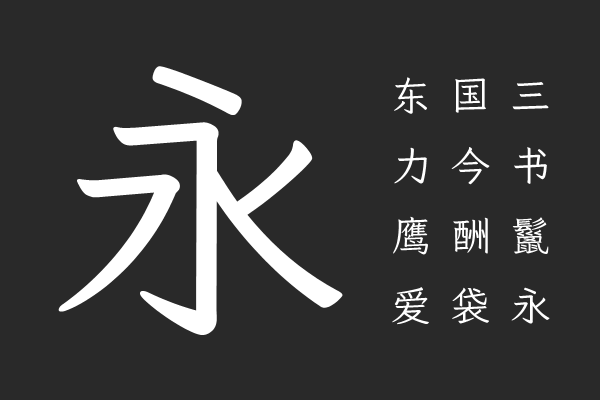
得意黑
得意黑它属于窄斜体,有点复古,有点未来感,造型非常独特。适合用在需要突出个性的标题、海报 Banner、数字展示。它不适合大段正文,但作为视觉焦点,效果极其出众。
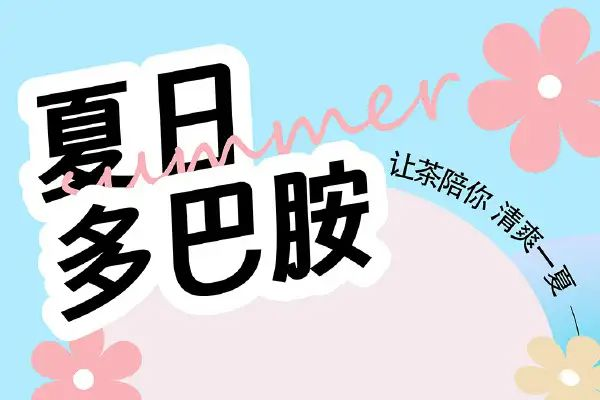
联盟起艺卢帅正锐黑体
联盟起艺卢帅正锐黑体是一款力量感很强的标题字体,笔画粗壮有力,充满自信。适合游戏、电竞、运动或男性化品牌网站的标题。用它做主标题,能立刻传递出强有力、果断的感觉。
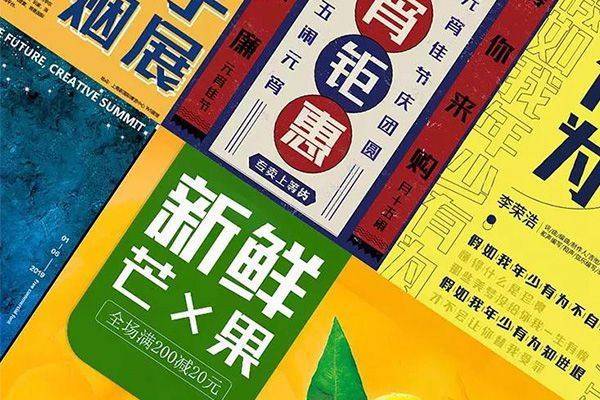
站酷快乐体
站酷快乐体笔画圆润,充满手写的随意感。适合儿童、母婴、休闲食品、社群活动类网站。用在按钮或一些提示性文字上,能增加页面的友好度和趣味性。
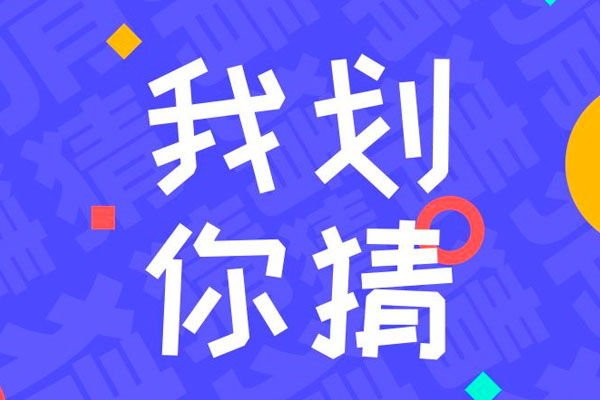
站酷小薇 LOGO 体
站酷小薇 LOGO 体是非常精致的一款字体,笔画细而有力,有点像高级品牌的 logo 常用字体。
适合用在哪儿:副标题、导航栏、卡片标题,或者需要体现精致感的短句。它能让细节之处也显得很有设计感。
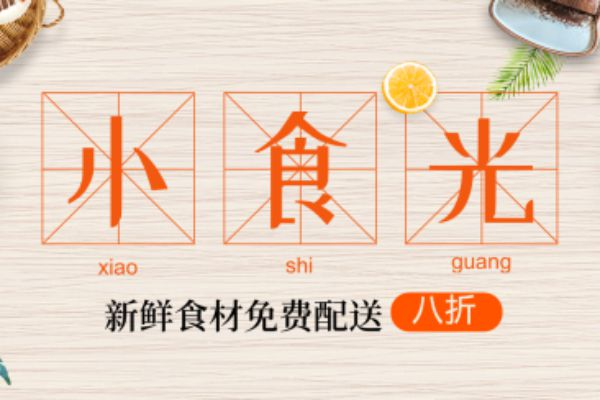
江西拙楷
江西拙楷体字体有真实的手写笔触,质朴又自然,能让人感受到温度。适合个人博客、独立设计师网站、手工艺品店铺。
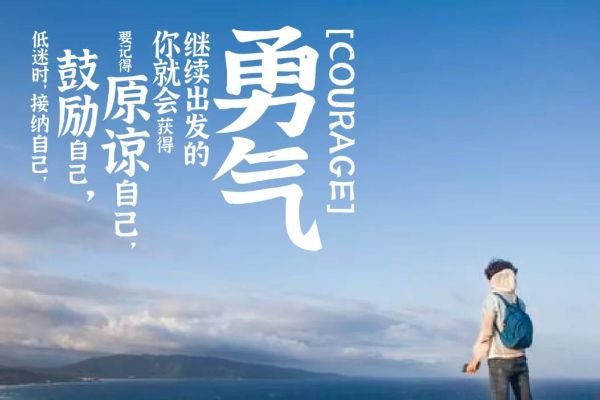
OPPO Sans
OPPO Sans是一款专门为屏幕阅读优化的字体。中宫开阔,字形均衡,长时间看也不会累。
适合内容量大的资讯站、阅读类应用、后台管理系统。它的核心优势就是极佳的屏幕可读性。
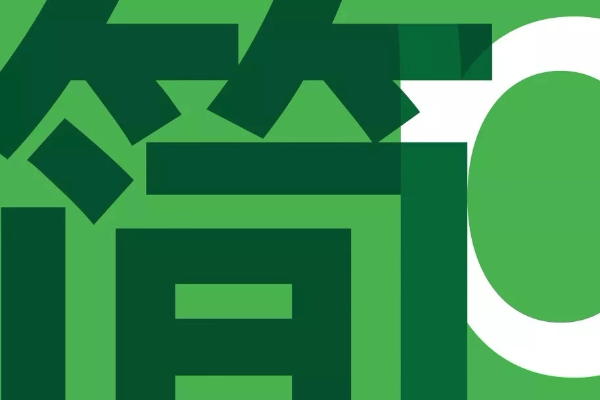
阿里妈妈数黑体
阿里妈妈数黑体是一款专门为数字显示设计的字体。数字的宽度统一,排列起来非常整齐、醒目。适合电商的价格展示、数据仪表盘、统计页面。当你的页面需要突出数字信息时,它是绝佳选择。
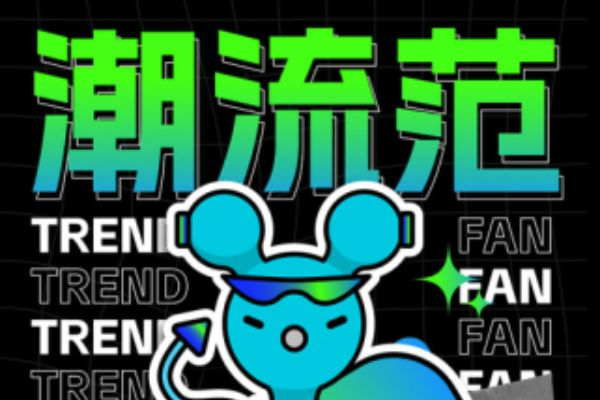
优设标题黑
优设标题黑专为标题场景的一款字体,字体挺拔,重心统一,排成一行时特别整齐、有气势。各类网页的主标题、Banner 大图上的文字都比较适合。它能确保你的标题清晰有力,富有现代感。
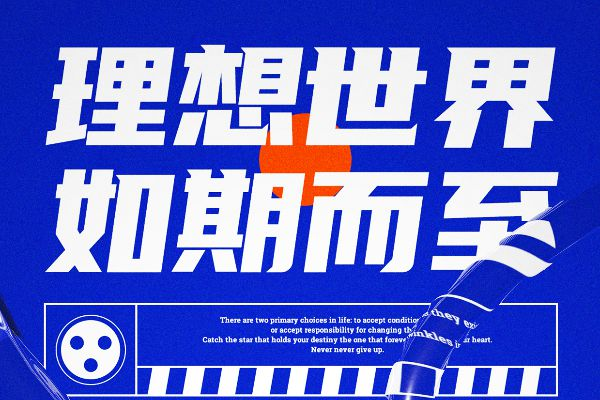
网页设计的字体使用技巧
注意字体的“性格”是否与品牌匹配。一个金融网站用“站酷快乐体”会显得不专业,字体的气质要和你想传达的情绪一致。
利用字重和字号创造层次,而不是增加字体种类。大多数优秀字体都提供从细到粗多种字重。通过调整同一字体的粗细和大小,你就能清晰地区分标题、副标题和正文,这让设计更整体、更专业。